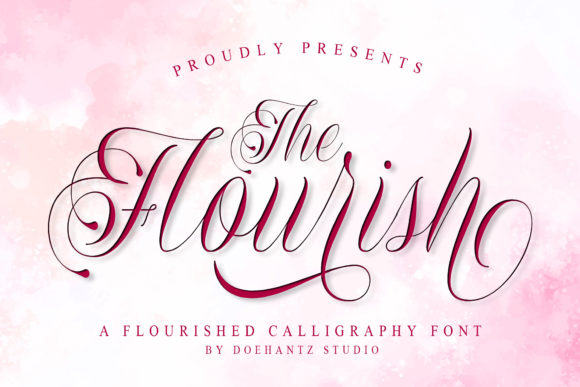
Flourish - это нестареющий и элегантный рукописный шрифт.
Он потрясающе смотрится на свадебных приглашениях, благодарственных открытках, цитатах, поздравительных открытках, логотипах, визитных карточках и любом другом дизайне, который нуждается в рукописном штрихе.
Он имеет изменяющуюся базовую линию, плавные линии, великолепные глифы и потрясающие альтернативы.